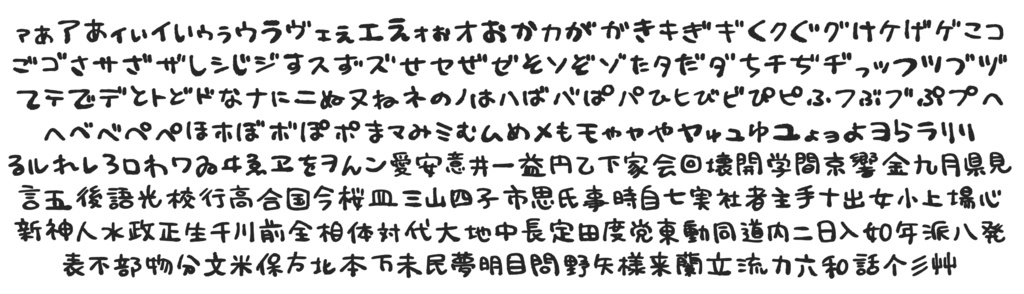
とりフォント
※本フォントのDLは無料で行なっていただけます。 製作者とり(別名義)の手書きフォントです。 Wing_font 制作中のおまけとして自分用に制作しましたが、 使い勝手が良かったためこちらもフリー配布することにしました。 フォントをインストールして頂くと、ワープロ、グラフィックソフトなどの アプリケーションでこのフォントを使って自由にデザイン、印刷することができます。 ■ご使用に際して■ 使用率が高い?とされる漢字が127文字入っておりますが相当少ない為、 ほとんど使う機会は出てきません。 フォントのテイスト的にも、ひらがな、カタカナ、欧文書体をメインに使用されることをお勧めいたします。 商用利用可能です。 ■免責事項■ フォントの使用について、いかなる保証も行いません。 発生したいかなる損害(データ損失等を含む)についても、提供側は責任を負いません 《!注意!》 当フォント入力中に、Adobe Illustratorなどの一部ソフトで勝手に小塚ゴシックになってしまう事象を確認しております。この問題の解決策として、 「イラレ職人 コロ」さんの「フォントが勝手に小塚になるのを防ぐ方法」 https://youtube.com/shorts/mxn8GXp8g58?si=XJ2C415ApkpBDXXp 上記の投稿を参照することで解決いたします。 ■製作者Twitterアカウント■ 魚(ギョ) @GyowaQ 最終更新日 2025/05/15